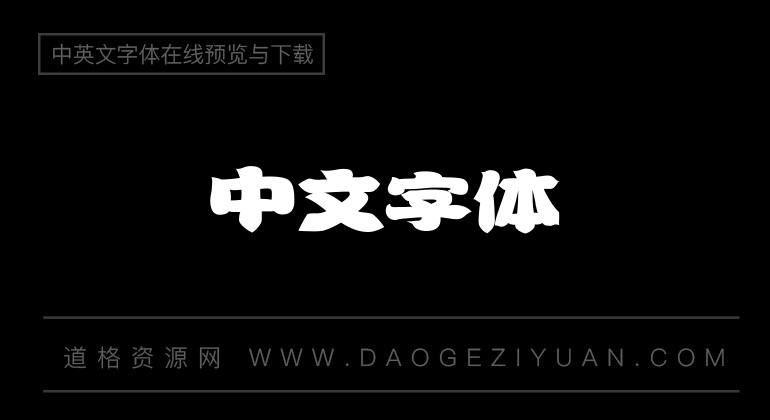
逐浪腴娃金鱼体
逐浪腴娃金鱼体是一款优雅的中文字体,它以独特的腴娃金鱼形状作为元素,具有清新而柔和的设计感,在细节处也有着独特的表达,适用于各类设计项目。
逐浪腴娃金鱼体是一款非常不错的手写艺术字体,具有很好的视觉感,适合于文化类的宣传设计、商业类品牌的广告和产品包装设计以及个性化文字排版等较多场景。